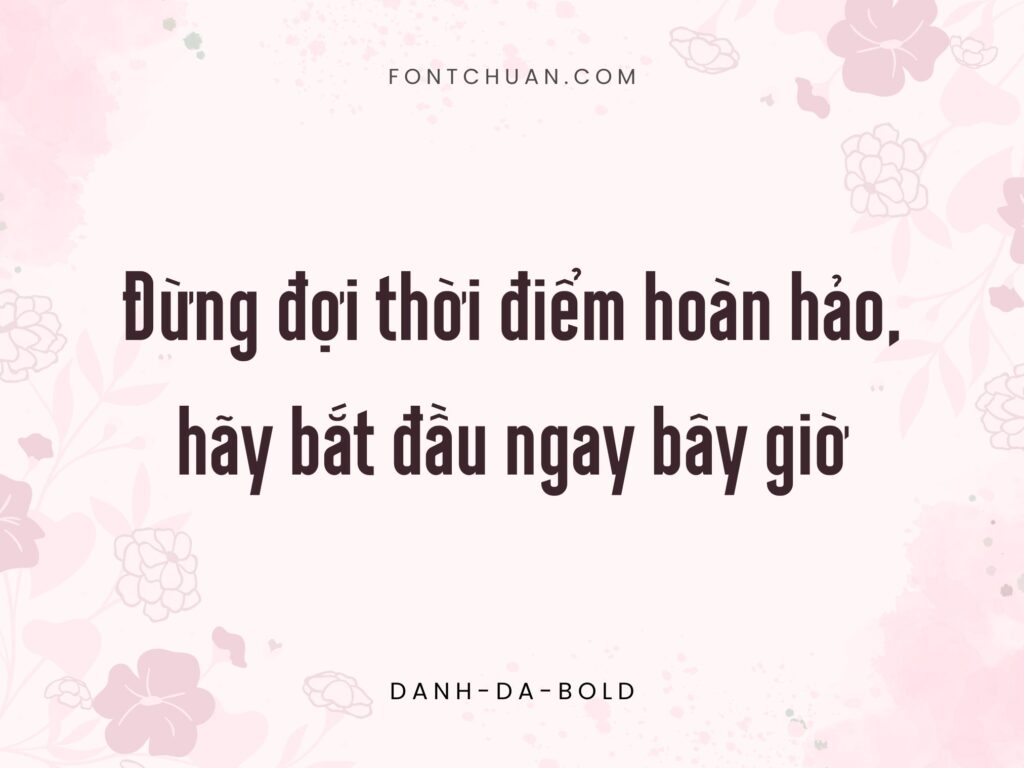
Font Danh Da Font Tiếng Việt
Danh Da, hay Đanh Đá, là một phông chữ Font Display đậm và cô đọng, mang dấu ấn của phong cách Art Deco từ thời kỳ Pháp thuộc, kết hợp với sự cứng cáp và mạnh mẽ của kiểu chữ tuyên truyền. Phông chữ này được thiết kế bởi Giang Nguyễn, trong dự án hợp tác với nghệ sĩ Hương Ngô cho tác phẩm “To Name It Is To See It” và nhận diện hình ảnh của cô. Đanh Đá là sự kết hợp từ nhiều tài liệu tham khảo khác nhau từ các tạp chí phụ nữ thế kỷ 20, tạo nên một kiểu chữ độc đáo và đầy cá tính.
Với các đường nét sắc sảo và cấu trúc chắc chắn, Đanh Đá không chỉ phù hợp cho các thiết kế hiện đại, poster hay nhận diện thương hiệu mà còn có thể ứng dụng như một Font chữ thiệp cưới độc đáo, mang lại sự mạnh mẽ nhưng vẫn tinh tế cho các thiết kế mang tính nghệ thuật và trang trọng. Phông chữ này miễn phí cho cả mục đích sử dụng cá nhân và thương mại, giúp người dùng linh hoạt trong việc áp dụng vào nhiều dự án sáng tạo khác nhau.